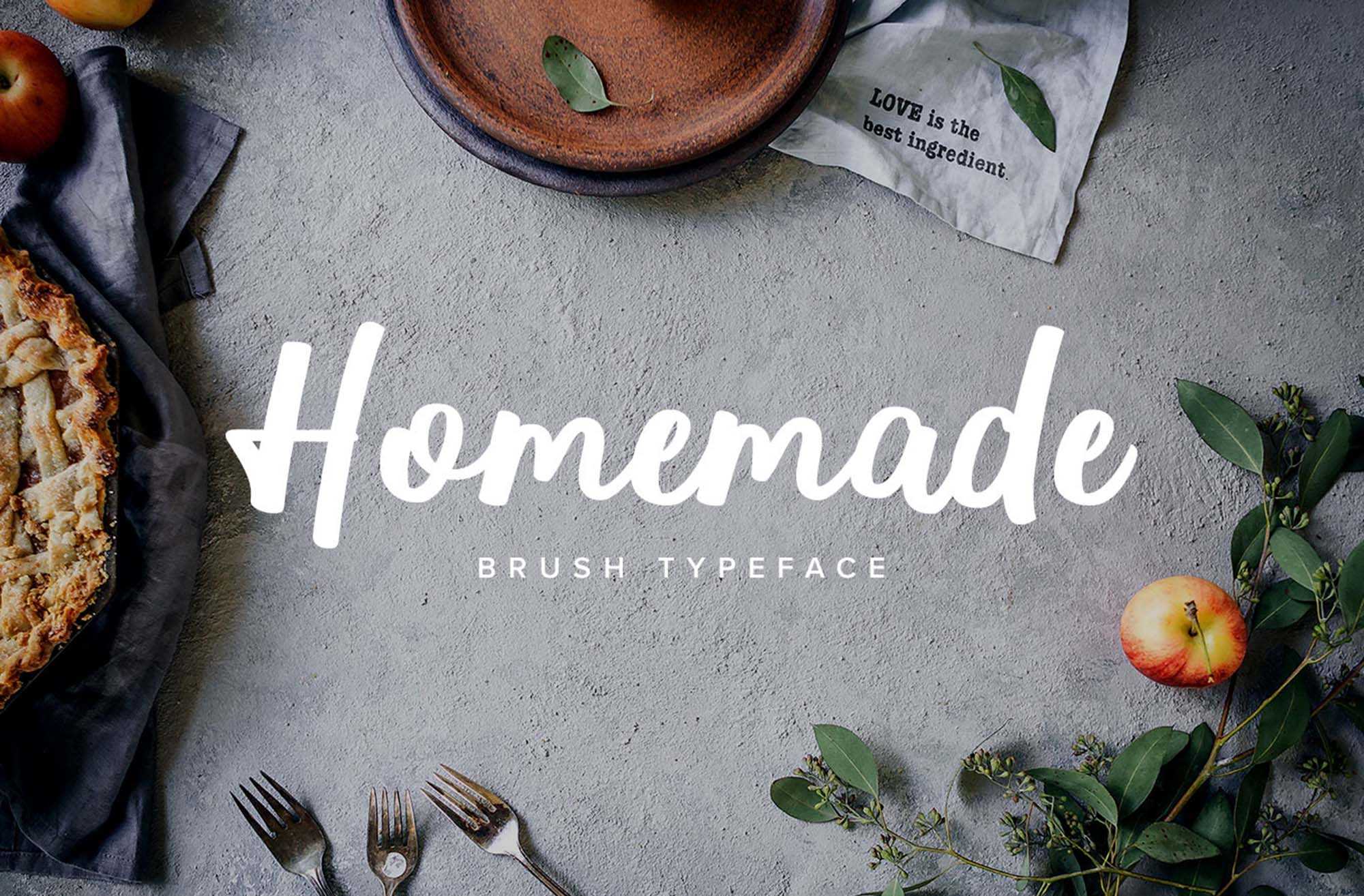
Homemade Brush Typeface – Download Grátis
Ao pensar em um pincel, a primeira coisa que vem à mente são os termos “leve”, “gentil”, “arte”. Este tipo de caneta caseira é exatamente o que um verdadeiro tipo de caneta deve ser. Ele trará uma leveza à qualquer projeto, transformando qualquer foto em uma peça de arte atraente para os olhos. O tipo de caneta vem em dois estilos, números completos, sinais de pontuação, acentos para todos os idiomas europeus, e por último mas não menos importante, inclui recursos de abertura (ligações para letras naturais dobradas e contextual para formas terminais casual). Seja em seu projeto de arte digital, sua página web ou sua publicação no Instagram, este tipo de caneta caseira é uma escolha perfeita para deixar um toque único e artístico.